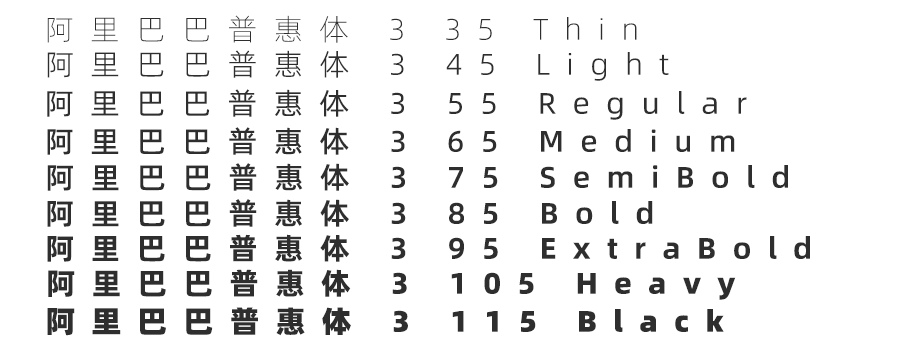
2款免费商用黑体字体家族推荐
在追求设计美感与商业合规的今天,选择一款合适的免费商用字体显得尤为重要。今天,为大家推荐两款优秀的免费商用黑体字体家族。
“有爱魔兽锐方”字体家族源自《魔兽世界》及《魔兽世界:经典怀旧服》的字体包,它不仅支持所有语言,还通过有爱锐方的字形微调技术,让文字边缘变得清晰锐利。这一字体家族共包含5种字重,能够满足不同设计场景的需求,为游戏玩家及设计师带来极致的视觉体验。
“阿里巴巴普惠体 3.0”是更具现代感的黑体字体家族。其中文字体采用简洁的笔画设计,造型偏瘦长,重心提高,完美展现了20岁阿里巴巴少年的精气神。此外,该字体在笔画上也进行了简化处理,如标题字省略出脚部分,更显简洁大方。家族中共有9款字重,为设计师提供了丰富的选择空间。